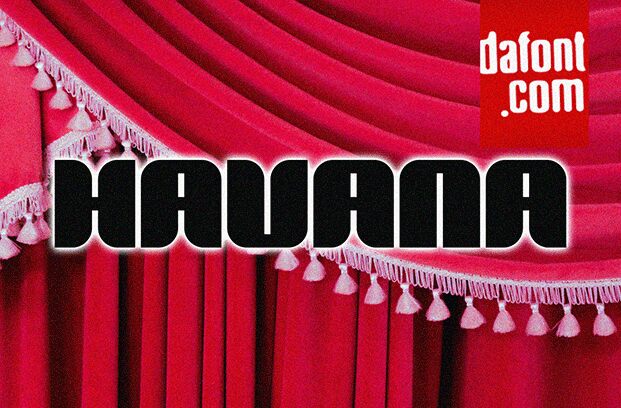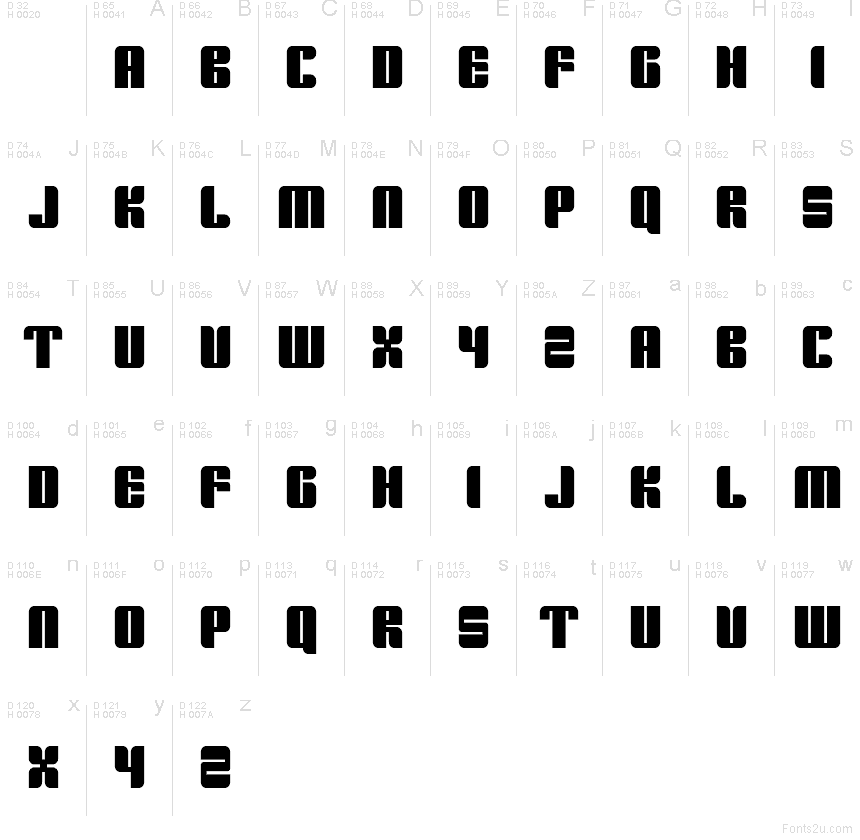
Havana Lorde, créée par Vladimir Nikolic, est une police d'affichage gratuite, ultra-grasse et géométrique, composée uniquement de majuscules, évoquant l'ambiance élégante et moderne des boîtes de nuit. Ses lettres imposantes, aux espacements serrés, mêlent arrondis extérieurs, coupes nettes et ouvertures verticales minimales pour former un bloc de texte dense.
Cette police gratuite est idéale pour les affiches de concert, les flyers de club, les pochettes d'album, l'image de marque dans la mode et les cartons de titres dramatiques. Elle donne le meilleur d'elle-même dans les titres courts et les textes de couverture, où son espacement compressé et ses espaces intérieurs étroits participent à une composition graphique percutante.